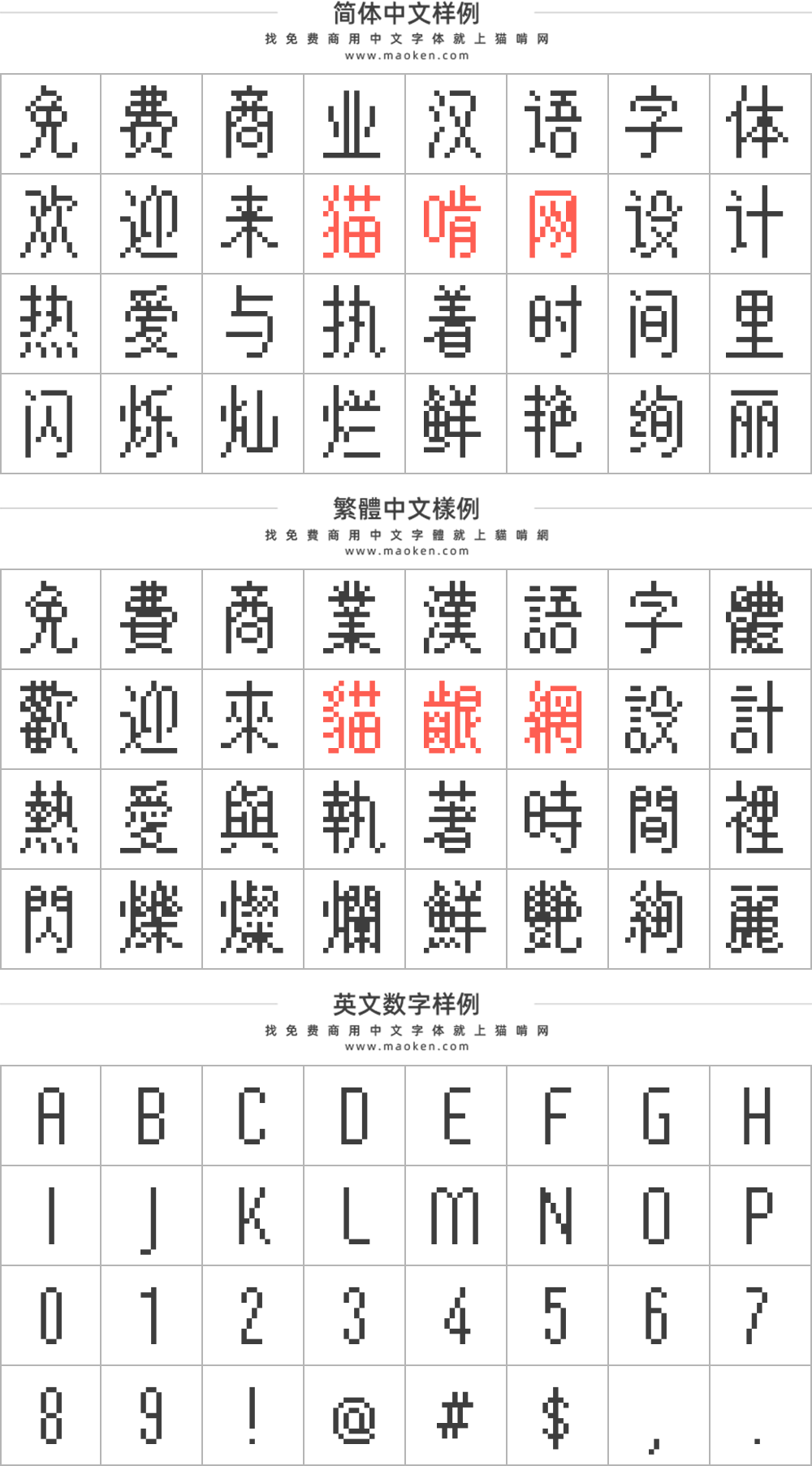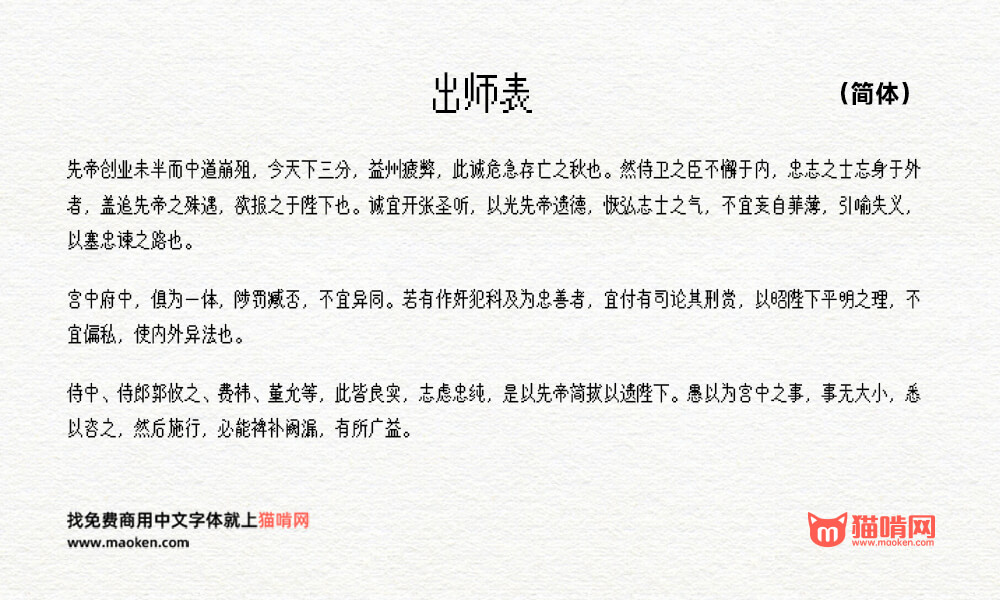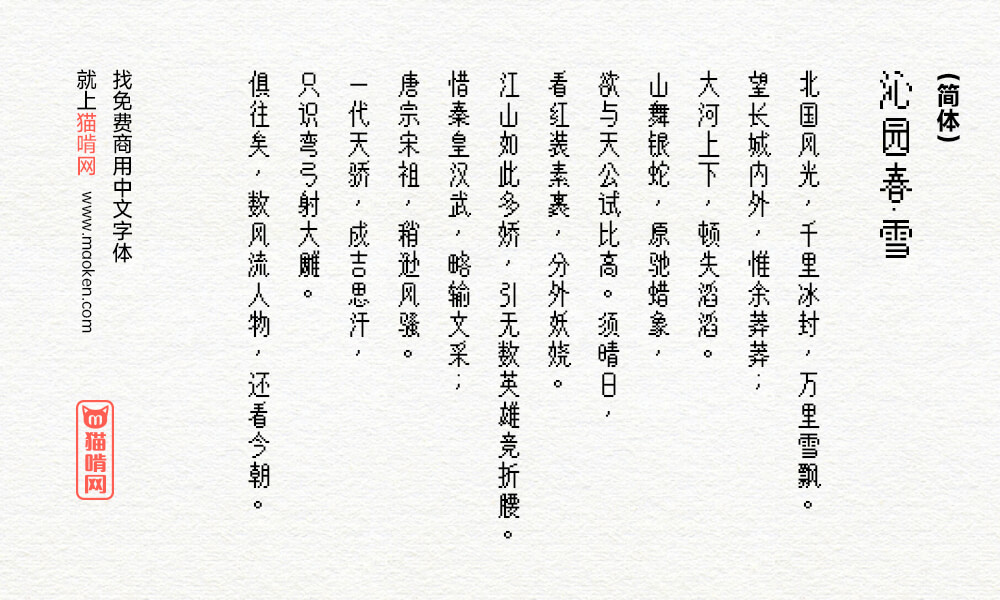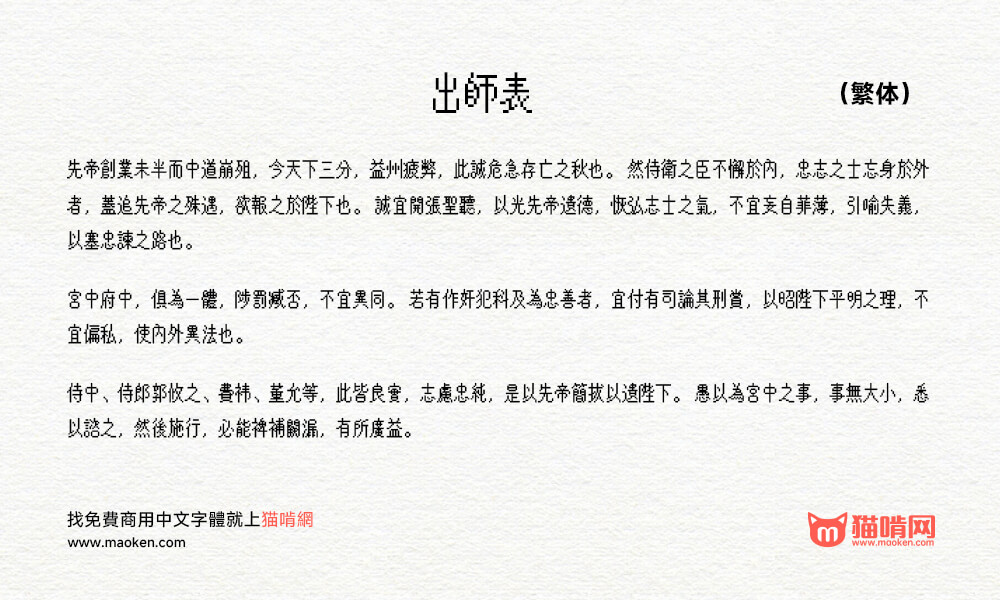
12×16莫妮卡圆像素:莫尼卡像素圆体补简计划
字体作者:綿雲飴里 (中国大陆) 字体字重:1个
某日本像素游戏(MORSOMNIA:0)用到了像素字体“x12y16pxMaruMonica”(猫啃有收:莫妮卡像素圆体),其特点为12×16的窄圆体,汉化组甚至找不到类似的中文像素字体。
注:虽说是“像素”字体,但原作不含点阵,字形实际是矢量勾勒像素块,使用时需将字号设为16px的整数倍以取得锐利像素效果。
看了汉化文本缺字统计,我觉得只缺六百多字的话,今年内应该是可以补完的,于是先做了个临时预览版(截至 Ver2025-5-30 只做了3百字,其它几百暂用类似日标字顶替,如“绘”,繁体为“繪”,我用“絵”),提前放出是吸引感兴趣的人参与补字。2025年6月18日补完游戏所需全部6百字,见下方字数统计
与原作的差异
“绘、絵”尚且码位不同,而日文的“冒(冒,U+2F8D2)、将、称、捨”等字与中文码位完全一致,字符上不能区分,于是我在保留原作字形、字序的前提下,在尾部追加了中式字形设为默认,给原字体字形添加了loclOT特性以备日区环境调用,例如浏览器遇到lang="ja"即可切换为原日式字形。
我感觉原作逗号做错了,但仍保留,并另作一个“中式逗号”
汉化组提供使用本字体效果(旧版)
额外添加了liga calt特性用于中文标点,例如在前述游戏里文字有勾边,原字体的破折号,眼尖的玩家能看见中间有断开,本改版则绝不会断:因为用liga将“——”替换为1个字符“⸺”
虽然我希望对原作无损修改,但其实改动了一字:口。原作里口囗完全一致无法区分,考虑到“口”占太满就上下缩小1像素,将“囗”设为口的日区字形。
“傻瓜偏旁”
也许有人要问,相比其它人的,此版补字有什么优势?我为此字研了一个技术:傻瓜偏旁。
新款造字软件如Fontra,对造中文有个奇妙的支援,是可变字体引申出的功能“智能偏旁”,比如在预先做好某偏旁最宽最窄两极端之后,就可以无级调节宽度、在所有包含此偏旁的汉字里复用它。
但像素字体不存在无级调宽——比如一般不许0.25个像素——我只能很傻瓜地预制了偏旁的每个需要的宽度字形以备复用。因ttf复用字形不太占文件体积,这导致我的字体比原作.ttf体积还小。
(旧版,2025-9-7版见此
参与补字者可以直接用预制偏旁肆意拼字,想想就爽🤪
伲呢坭妮抳昵柅狔秜胒蚭跜铌
显然尼旁分为两部分更方便
另外,还补充了多重映射:⤹⤸ⒶⒷⓍⓎ⮹⨂⊚🟗🟕⌨⊝⨁➖➕⌂,这些是原作就有字形但放私用区的。而原作中特地放私用区的游戏符号皆在本作中保持一致。
晩(晚)像素里不必区分也合并映射了,但若你的游戏里有意要区分这2字的话也请告诉我。
也没经过几个月,元素周期表已于2025-7-15版补全了……仍期待大家参与(旧版字体)
2025年8月3日起,包含全部藏文,并针对一些词汇单独编写了特性。但注意藏文需要高级排版,由于原日文字体天然的度量限制,恐怕难以按正确规则排版藏文。下图右下角展示了 不支持→支持 排版特性的情况。
适当复用字形以无损压缩,支持超17000字符:玲琍蹀躞猞猁姵君动辄哎呦喂㧟(擓,㨤)一勺奾㛉𡞞噍吧哖𫐓以为轮假꯭下꯭划꯭线꯭
• 添加:𠄞𠄟𠄠𠄡丆王𢀓丒𫝀屮𫡃乆𫠠𢖩𣥂𡯃𠫓𫝅冚𨙨𱰜㲽泐洐烆珩绗胻鸻𱉢𬣦呦坳岰怮柪狕眑聈蚴袎靿泑溭𰊐谡𰵚𫐉衑𲌅𬳴𰹽辄踂𰽿𫚚𦔮者䂖𲳉𢍺𰒷𱢾㲺㳡挝𢯊啲哋嘅嗰哖姩脌鵇鴝欨邭𰬆𰵛𰺁呴坸姁昫泃玽眗竘胊{与朐区分在⺼旁}蚼袧跔𲃫跐呲泚玼皉骴龇佌仫䶸呧坻弤彽怟泜眡秪蚳袛诋阺骶𰷢𰺀鸱鵨倽涻𱅚猞犼猁唎娳梸浰琍脷𨐈𰽵𫘡𬘢䌶𠆫𠆧𠆨𠆮𠆯𠆩㐹傥谠镋𣺼𪤅𣗋𬊵𤆣𢎽𤜯𥄫𲂅𱅂𩽹﨤𳂷﨣呌斢枓炓酙钭阧酀䜩嬿曣觾𱅬𤣽㺨𫟉厸䏧腵㗇䠍嘏婽徦椵溊煆犌猳睱碬𩐀豭貑倷㖠㮈㴎㓇𫍚㤇㕭叱呺𠳯枵杻吜沑炄粈靵𫥞㧩䊃姵㚭𡟵㜓㟷𫶇崡蜬𱂰𭡝㖤䘶㮀𣓣𣶮𠩋𱐝婲𰔀㬸㳸哷捋浖脟蛶酹锊虢偗渻𡞞媃楺渘煣猱瑈腬蝚𫔄𱅟𬶧𫐓伆圽岉昒朆歾沕粅肳覅𧟰𱅜偠喓婹崾楆㶧熥嗵嚅壖嶿擩曘檽燸獳瓀礝穤羺醹隭𦈡𱈗𰶌𰿂颥噇墥徸曈朣燑犝獞疃穜膧{与朣区分在⺼旁}蹱勭氃𦒍躞㦪㰔𤫉㽊㮸𠌡𢱤𩠌𱠥𲕸𣏌杞𡉏𢩽𤣱𥝗𬜒𱞁㤈𱞫怴泧狘眓钺𫑛𨒋𬱸𱥟魆戹帍戾蟕𣚀𪬰𲚏𰽰𬱙𮖱𮲺𧹖觍𦮉𫞉㧕𪭢𩉜𫝃𮱸㓠屇阗囯𣎴ƵƶDŽDždžLJLjljNJNjnjǞǟǠǡǤǥǦǧǨǩǮǯǰDZDzdzǴȀȁȄȅȈȉȌȍȐȑȔȕȞȟȠȦȧȪȫȮȯȰȱȲʘṀṁṄṅẘẙ˘˜ⁱᵢₙϽϾϿͻͼͽϒϓϔϖ🔲◻◼◽◾▫▪⸨⸩│○⇵꯰꯭
• 修改:丅𡴮𢀕叾吖啥𠯸𮳞㞌误敟衈钑彋𫑛怴狘眓钺泧测涏泮眫翢翮翲翙翗夠岣朐翑豞豿雊驹鸲鼩齁𬶋𫞮癿皦皫皜
• 多重映射⸺
• ȳ͵ɸͶͷͿϳϷϸϹϲƆɔↃↄϴɵϵ϶əǝɜ■⼾⽰䶹𧺯𢛔玥糨吆
• 仅对原作缺对应繁体的简化字繁入简出:“貾軧軯駍嗎驠騕騇駖軨詅訞詊鉡頖顄顬鱬譳鑐鏻鎶𫟰鎝鎲鋝鈄鍒騥鰇輮摐擓纕䊷賟覥紌訧魷詏鴢鴴輄銧駫餸絇訽軥鮈鈒訯馺魥鮿銸倈㑶齜䪗䬂鞿閩彞”→“𰷢𰺀𰹽𬳴吗𱅬𱅜𱅚𲌅𫐉𰵚𫍚𫟟𰽰𬱙𱂰颥𱈗𰶌𰿂𬭸鿔铛𨱏镋锊钭𫔄𱅟𬶧𫐓𪭢㨤𬙋䌶𧹖觍𬘕𰵎鱿𬣦𱉢鸻𨐈𰽵𫘡𩠌𰬆𰵛𰺁𬶋钑𲂅𱅂𩽹𫚚𰽿俫㐹龇𩐀𬱸𩉜闽彝”
• 日式简化字“𫠚”→“齣”
• 修正原作问题:圆像素的减号“−”(u2212,非“-”)是全角,字形与“-”完全一致,且与“+ ±”(皆为宽5px,顶格)不搭配,这一版起改为宽5px顶格。若排版需沿用旧版,批量替换为“-”即可;局部开启`fwid`或局部`locl`切换为`jp`亦可。
• 补充或更改特性⸺
• locl:中式“少伶冷怜玲聆蛉囹嘴戻曾岼怦秤泙滞拌胖袢判叛−{u2212}”,日式字形重定向→/uEC11/uEF36冷怜玲聆/uE6C9囹/uE634/uE23B/uE6FE/uECBC/uF026/uE9E4/uECD9/uEEDE/uE2CC/uE0D6/uE8A2/uE224/uE3DB-
• 汉字上下文移位kern:{声杜鹃}{颈斑鸠}{山斑鸠}{下꯭划}{下划}
• subssups:in→ⁱᵢⁿₙ{其它字符上下标形式暂无考虑}
• 调整查找顺序,参考 unicode.org/charts/PDF/UFF00.pdf 列举如下{但设゙゚⸨⸩的全角形式为゛゜⦅⦆}
• hwid涉及:0~9 ←↑→↓<>?ヲァィゥェォャュョッーアイウエオカキクケコサシスセソタチツテトナニヌネノハヒフヘホマミムメモヤユヨラリルレロワン゛゜│■○
• pwid涉及:0~9 A~Z a~z 〜!"#$%&'*+,﹐{uFE50}-./:;<=>?@\^_`|~¢£¬ ̄¦¥₩⦅⦆
• fwid涉及:0~9 A~Z a~z ←↑→↓−{u2212}!”#$%&'()*+,-./:;<=>?@[\]^_`{|}~¢£¬¯¦¥₩ヲァィゥェォャュョッーアイウエオカキクケコサシスセソタチツテトナニヌネノハヒフヘホマミムメモヤユヨラリルレロワン゙゚│■○⸨⸩
• 已知问题:考虑到大多数人从未听说标点SVS(Standardized Variation Sequences)更不会用,未予支持,确有需求请找我。
Ver 2026-01-01(2026/01/01)支持:悻然浏览棕榈榫卯¹⸍²《百度文库一万普通人姓名》白芷、周筠、坣娜、𤨒晶……相关字体设计笔记
• 添加:㇒𬺹𬺲𬺴丄丅𮯰𬂛𬺰𬺱𫝄冇曱甴榈榫𢲜𣯍𪄩𦞠𮲫膌塉嵴鹡𮵮笇筠𭖠荺芷芏𫇭忭汴炞犿玣𮴆瑺龦𮸟𰊠𡎚𡐓𪣻𲘞𨸙嗲𠯸𮳞𱝫𱎺伖鿆犮冹坺妭帗柭炦绂胈蛂袚钹韨馛鲅鼥沷潇𤎻𫾃𰘩蟏䅰𡟯𢞴𤨒𪩊𫣆𬃼𬻹𱴨𮸚煾𰜩浏𭇯𰂁𰑙伈吣抋杺𲇴𮸌𰾽瞩𡠟𧜭𨅛𪹳𭲫冁搌榐蹍辗𫐐羗唴猐琷蜣睪婞悻涬啈𠿬𠻦𥊙𫱆𮸕𩧿䌿𠡀𭐞𱘣厺厹叴旮勼𬱓旯宄艽芄𲶷𱣋𥖨𮀔𱍐𫝁𫝆𫝇𫌀𪟝𪨰𮷊𠅤𠙶ⁿ⸍↊↋⥚⥛⥜⥝{形如倒转1的箭头}⥞⥟⥠⥡🔘ⓘ
• 修改:刁习屴竻艻勡垦恳峎处雵乭搂菇𲘿甭(改nefa fshr作)
• 多重映射⸺
• ӏꞵꟛ𱢹{胿不必区分作⿰⺼圭}書
• 25151r-katakana-ne-wi.pdf 临时补充异体假名𛄧𛄨,之后版本修改
• 仅对原作缺对应繁体的简化字繁入简出:“囅钃𨪜鏛鈊釚頄懰鰏鍢䮠䋹紈紱鈸韍鮁餄餎”→“冁𰾽𮸚𮸟𲇴𫟲𬱓𰑙鲾𮸕𩧿䌿纨绂钹韨鲅饸饹”
• 补充或更改特性⸺
• aalt:❶自制“嘱”,原作不佳字形重定向→𰇰(至此6个字有原作alt字形:唏喃嘱媒昵硼);❷“垦”异体→/uF7A6
• locl:中式“才卞抃拔祓秡跋”,日式字形重定向→/uE24D/uE35E/uE283拔/uE953/uE9E1跋
• 汉字上下文移位kern:{猛犸象}{该账号}{号已被}{被封禁}
• 打鱼.fshr
• 添加:兹荫佥奂弈橐璺壆甯甭瞢窬簋𲘿坣
• 修改:蘑
Ver 2025-10-24(2025/10/24) 支持:临澧褒姒傈僳松鼠撅鱼鸳鸯仇雠糨糊水黾……覆盖《现代汉语常用字表》3500字。
太棒了,好漂亮,好有以前的gba游戏的风味